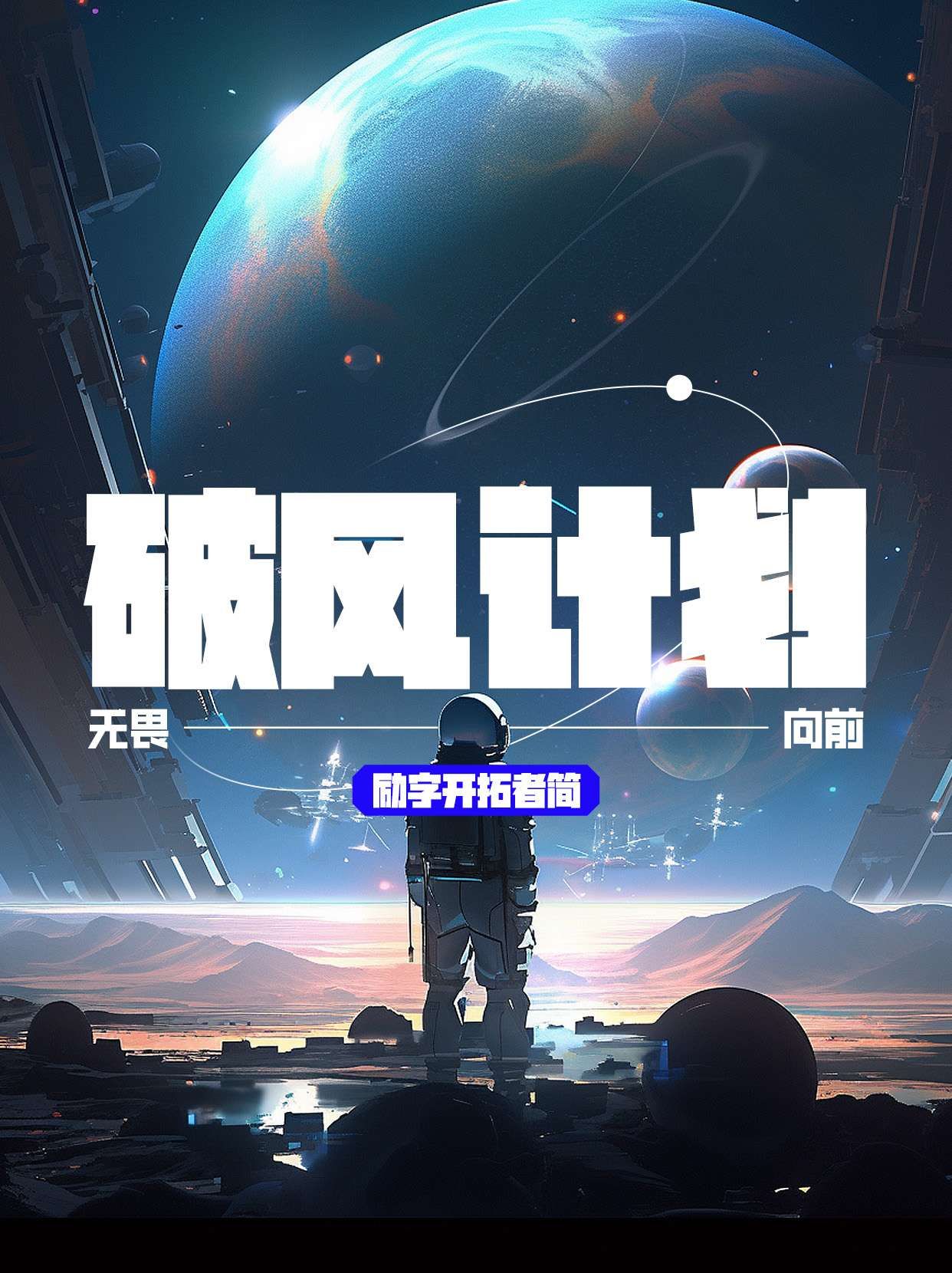
Logo设计中的字体瑰宝:四款精选字库字体推荐
在Logo设计中,字体选择至关重要。它不仅能够传达品牌的核心价值和理念,还能增强品牌的辨识度和记忆度。今天,我将为大家推荐四款适用于Logo设计的精选字库字体,它们各具特色,能够满足不同品牌和场景的需求。
第一款推荐的是“励字开拓者简 超级黑”。这款字体字型方正,中宫较大,重心适中,整体给人一种稳重而不失活力的感觉。其笔画简约,横平竖直,棱角分明,带有强烈的镜像视觉效果。这款字体不仅适用于标题,还能平滑过渡到正文,满足各场景的应用需求。特别值得一提的是,它还包含了常用的网红流行用字,如“又、双、叒、叕”等,让你的Logo设计更加与时俱进。
第二款推荐的是“励字志向黑简 常规”。这款字体融合了圆体与黑体的特点,在稳重中增添了一丝灵动。其笔画拐角采用适当的外圆角处理,使字体字面充实,结构稳定,更适配屏显的使用。这款字体适合那些希望传达出稳重而又不失活力的品牌形象。
第三款推荐的是“造字侠磅礴简繁”。这款字体中正感官丰富,运笔富有节奏感,笔画粗细变化明显,转折方圆相结合,呈现出一种独特的艺术美感。它适合那些希望打造具有文化底蕴和艺术气息的品牌形象。无论是中文还是繁体,都能在这款字体中找到合适的表达方式。
最后一款推荐的是“励字圆梦简 中黑”。这款字体字型圆润柔和,笔画为直线笔画,以竖折笔画代替部分弧线,简洁明了。其笔画起笔、收笔和转折处融合圆体自然的圆弧风格,中宫松散,外圆内方,既具有现代感又不失亲和力。这款字体拥有三款字重,适用于标题和正文,能够适配多种风格与样式的排版需求。
以上四款字体各具特色,无论是稳重、灵动还是艺术、现代感,都能在这些字体中找到合适的表达方式。希望这些推荐能够帮助你在Logo设计中找到最适合的字体,打造出更具辨识度和记忆度的品牌形象。